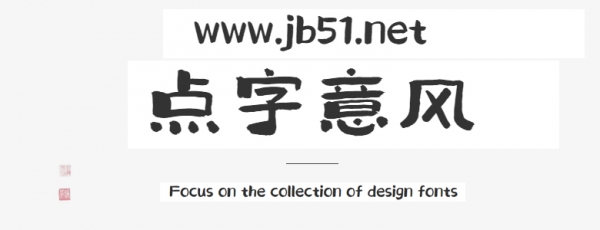
點(diǎn)字意風(fēng)是由點(diǎn)字庫(kù)推出的藝術(shù)字體,這款字體筆觸略顯粗實(shí),字形圓潤(rùn),具有很好的視覺(jué)感,適合應(yīng)用于藝術(shù)設(shè)計(jì)、各類廣告和產(chǎn)品包裝設(shè)計(jì)等領(lǐng)域。